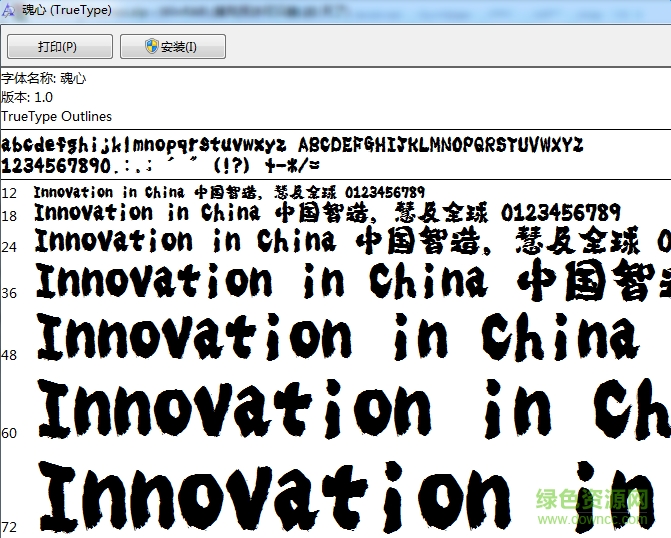
konshin英文字體
konshin字體是一款超好用的個(gè)性英文字體,該字體對(duì)于從事平面設(shè)計(jì)的朋友來(lái)說(shuō)是一款不錯(cuò)的個(gè)性字體,能夠幫助設(shè)計(jì)更具個(gè)性,需要的朋友可以來(lái)綠色資源網(wǎng)下載使用!
konshin字體
小編測(cè)評(píng)
konshin字體是一款極具個(gè)性的字體,該字體十分飄逸,彰顯了自己的個(gè)性,有喜歡的朋友可以來(lái)綠色資源網(wǎng)下載使用!